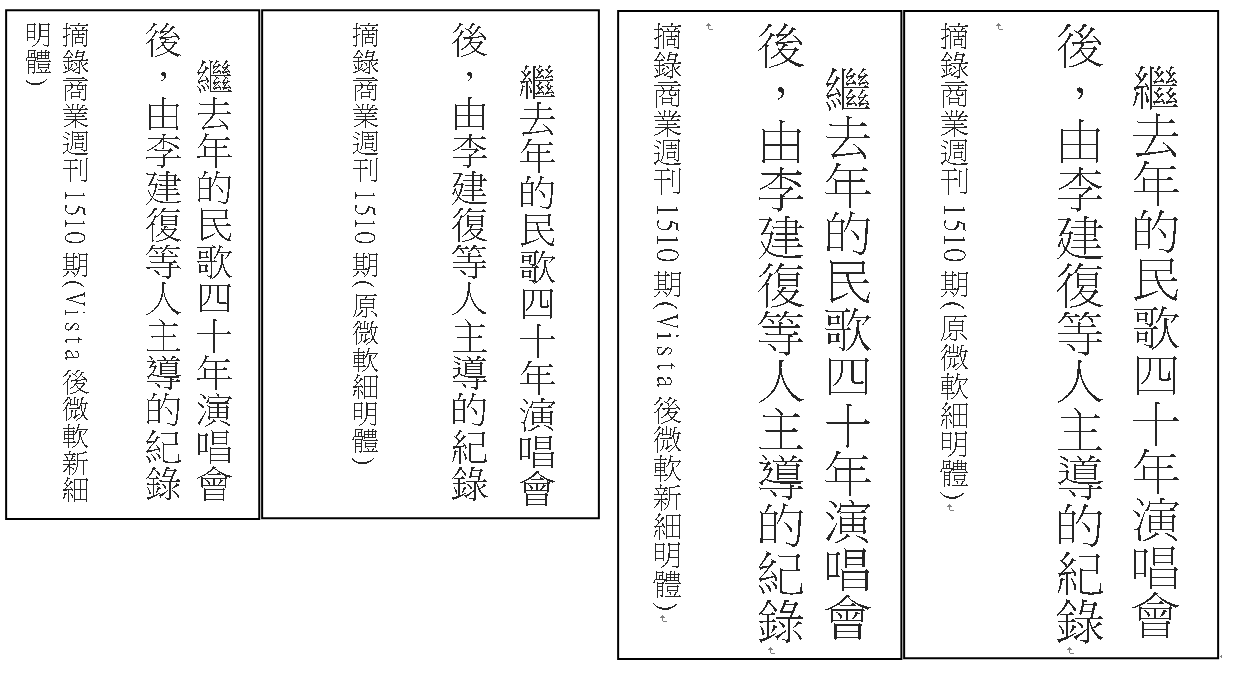
本來是依照康熙字典寫法的本蘭明朝體,轉為微軟細明體,並延續 JIS 的印刷寫法,但在幾年前微軟 Vista 發表之後,在未告知大眾的情況下,將系統字新細明體改成教育部標準宋體寫法(在日本稱教育用寫法字體為學參用字),因此已失掉日本寫研本蘭明朝體的印刷字體之美,成為失去平衡的手寫筆法字體,印刷界相當排斥,目前觀察到商業週刊內文仍以舊版新細明體來呈現。